印刷物を作るうえでどのフォントを使ってデザインをするかは重要な要素となります。しかし、フォントのことって知ってるようで知らないこともたくさんありますよね。そこで、今回はフォントの基礎知識や印刷物に適したフォントの選び方を徹底解説します!
また、特別なフォントを持っていなくても、通常のWindowsやMacのパソコンに入っている使えるフォントもご紹介いたします。
フォントとは?どんな種類がある?
そもそもフォントとは、共通のデザインで作成されたひと揃いの文字の集まりのことを指します。似た意味で「書体」という言葉もありますが、デジタル化された書体のことをフォントと呼ぶようになりました。
例えば、Wordでよく使われる「MS Pゴシック」「MS P明朝」などは全てフォントの一種となります。
大きくはゴシック体と明朝体の2つのグループに分かれ、それぞれで様々な表情を持ったフォントが存在します。ゴシック体にするか、明朝体にするかで違いが出るのはもちろん、同じゴシック体の中でもフォントによって印刷物の印象は大きく変わってきます。
また、フォントは種類だけでなく、サイズ、太さ、色などによっても印象や見やすさ、読みやすさは変わってきます。インパクトを重視するあまり、見づらくなってしまうということはよくありますので、フォントを選ぶ際やデザインで使う際には注意しましょう。
印刷物に適したフォントは?
印刷物に適したフォントの選び方を見ていきましょう。
チラシ、リーフレット、ポスターの見出しやキャッチコピーにはゴシック体
チラシやリーフレット、ポスターなどの見出し、キャッチコピーなど、インパクトを持たせたり、力強さを出したりしたいときにはゴシック体がオススメです。ゴシック体は視認性が高く、太字にしてインパクトを出しやすいフォントが多くあります。
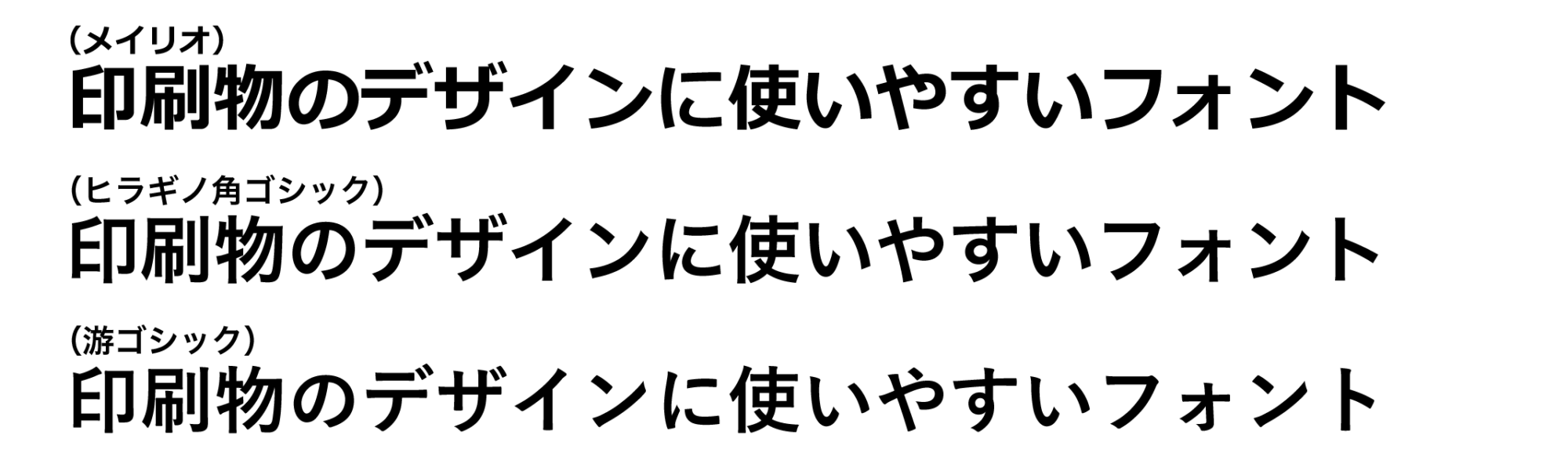
特に使いやすく、判読性も高いのが「メイリオ」「ヒラギノ角ゴシック」「游ゴシック」です。
メインとなる見出しやキャッチコピーは思い切ってサイズを大きくしたり、太くしたりするとデザインにメリハリが生まれます。
長文のあるリーフレットや会社案内などの小冊子の本文には明朝体
明朝体は全体的に線が細くスリムな印象で、長文のデザインに適しています。そのため、長文があるリーフレットや会社案内など読み物系の小冊子の本文に使われることが多くあります。本文を明朝体で、ページタイトルや見出しをゴシックでデザインする手法もよく見られます。
オススメの明朝体フォントは「ヒラギノ明朝」「游明朝」などです。
本文のフォントは小さくしすぎると読みづらくなってしまいます。高齢者を対象とした印刷物ではサイズを大きめにするなど、工夫をするとよいでしょう。
個性を生み出す筆書体や手書き風フォント
筆で書いたような趣のある印象を生み出す筆書体というフォントもあります。全てを筆書体とすると読みにくくなりますが、見出しやキャッチコピーでアクセントとして用いることで独特の雰囲気を生み出せます。格式が高い、伝統的、高級感といったイメージを演出したいときにうってつけです。
ペンで手書きしたような手書きフォントも、個性を生み出すためによく使われます。可愛らしさ、親しみやすさを演出するために使われることが多く、子ども向け、ファミリー向けの印刷物で活躍するでしょう。
例えば筆書体であれば「HG行書体」、手書きフォントであれば「ZEN紅道」というものがあります。このような書体は、元々パソコンに入っていない場合があります。その場合は、Googleフォントなどで探してみるというのも方法の一つです。
多くの人が分かりやすい、読みやすい「UDフォント」も大切
高齢化に伴い、細かな文字、小さい文字が読みにくいという人が増えていたり、社会全体で多くの人にとって暮らしやすいユニバーサルな社会を目指す背景から生まれたのが「UD(ユニバーサルデザイン)フォント」です。
UDフォントでは、見間違いをできるだけ少なくするようなフォントの作りになっています。例えば、「6」という数字を「8」と見間違えないようにするために、アキの部分を多く取ったり、「8」を視認性の高い形状にするなど様々な工夫が凝らされています。
町の広報誌や掲示物、駅名の看板、医療や福祉の現場で使われる印刷物など、私たちの身の回りで多く使われています。UDフォントを使うことで、多くの人に伝わり、思いやりのある印刷物の制作に繋がります。新晃社では、UDフォントを導入したデザインを行っておりますので、気になる方がぜひご相談ください。